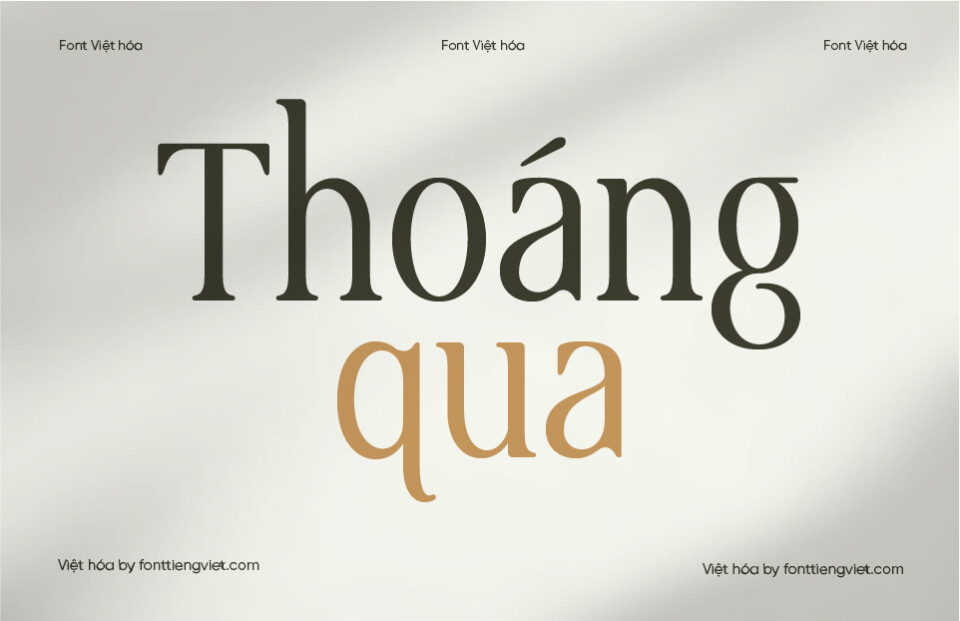
Font Việt hóa 1FTV VIP Tropic Fantasy
Tải Font Việt hóa 1FTV VIP Tropic Fantasy – Nét Chữ Nhiệt Đới Đầy Ấn Tượng
Giới thiệu về Font Việt hóa 1FTV VIP Tropic Fantasy
Trong thế giới thiết kế đồ họa hiện đại, việc tìm kiếm một bộ Font Miễn Phí chất lượng cao và phù hợp với ngữ cảnh là điều vô cùng quan trọng đối với các bạn học sinh và giáo viên. Font Việt hóa 1FTV VIP Tropic Fantasy nổi lên như một lựa chọn hàng đầu cho những ai yêu thích phong cách trẻ trung, năng động và mang hơi thở của mùa hè nhiệt đới. Bộ phông chữ này không chỉ đơn thuần là công cụ soạn thảo văn bản mà còn là nguồn cảm hứng sáng tạo vô tận cho các dự án học tập, trình chiếu slide bài giảng hay thiết kế poster sự kiện trường học. Với các đường nét uốn lượn mềm mại nhưng vẫn giữ được sự chắc chắn, bộ font này giúp thông điệp của bạn trở nên nổi bật và thu hút ánh nhìn ngay từ giây phút đầu tiên.
Đặc điểm nổi bật của Font Việt hóa 1FTV VIP Tropic Fantasy
Thiết kế độc đáo và hiện đại
Được thiết kế với tư duy đột phá, Font Việt hóa 1FTV VIP Tropic Fantasy sở hữu cấu trúc chữ cái độc đáo, kết hợp giữa sự phá cách và tính thẩm mỹ cao. Các ký tự được chăm chút tỉ mỉ để tạo nên một tổng thể hài hòa, phù hợp với các chủ đề về du lịch, thiên nhiên và giải trí. Đối với các bạn học sinh đang thực hiện báo cáo ngoại khóa hoặc thiết kế bìa tập san, bộ font này sẽ mang lại vẻ ngoài chuyên nghiệp và đầy cá tính. Các nét chữ dày dặn giúp việc đọc nội dung trở nên dễ dàng hơn ngay cả khi được in ấn trên các khổ giấy lớn hoặc trình chiếu trên màn hình máy chiếu tại lớp học.
Khả năng tương thích và tối ưu hóa
Một trong những ưu điểm lớn nhất của Font Việt hóa 1FTV VIP Tropic Fantasy chính là khả năng hiển thị tiếng Việt hoàn hảo. Đội ngũ kỹ thuật đã tinh chỉnh các dấu thanh một cách khéo léo để không gây ra hiện tượng chồng chéo hoặc mất cân đối, vốn là lỗi thường gặp ở các bộ font ngoại quốc. Phông chữ này hoạt động mượt mà trên nhiều phần mềm thiết kế phổ biến hiện nay như Canva, Photoshop, và cả các ứng dụng văn phòng cơ bản như Microsoft Word hay PowerPoint. Điều này giúp các thầy cô giáo dễ dàng tạo ra những tài liệu giảng dạy sinh động mà không gặp phải bất kỳ rào cản kỹ thuật nào.
Ứng dụng thực tế trong môi trường giáo dục
Việc sử dụng Font Việt hóa 1FTV VIP Tropic Fantasy trong nhà trường mang lại luồng gió mới cho công tác truyền thông nội bộ. Thầy cô có thể dùng font chữ này để làm tiêu đề cho các bảng tin thi đua, tạo thiệp mời cho lễ bế giảng hoặc thiết kế các chứng nhận khen thưởng cho học sinh đạt thành tích tốt. Sự vui tươi của bộ font giúp giảm bớt căng thẳng trong học tập, tạo ra môi trường thân thiện và khuyến khích tư duy đổi mới. Học sinh cũng có thể tự tay làm những video thuyết trình ấn tượng hoặc các trang cá nhân trên mạng xã hội mang đậm dấu ấn riêng nhờ vào sự đa dạng và linh hoạt mà bộ phông chữ này mang lại cho người dùng.